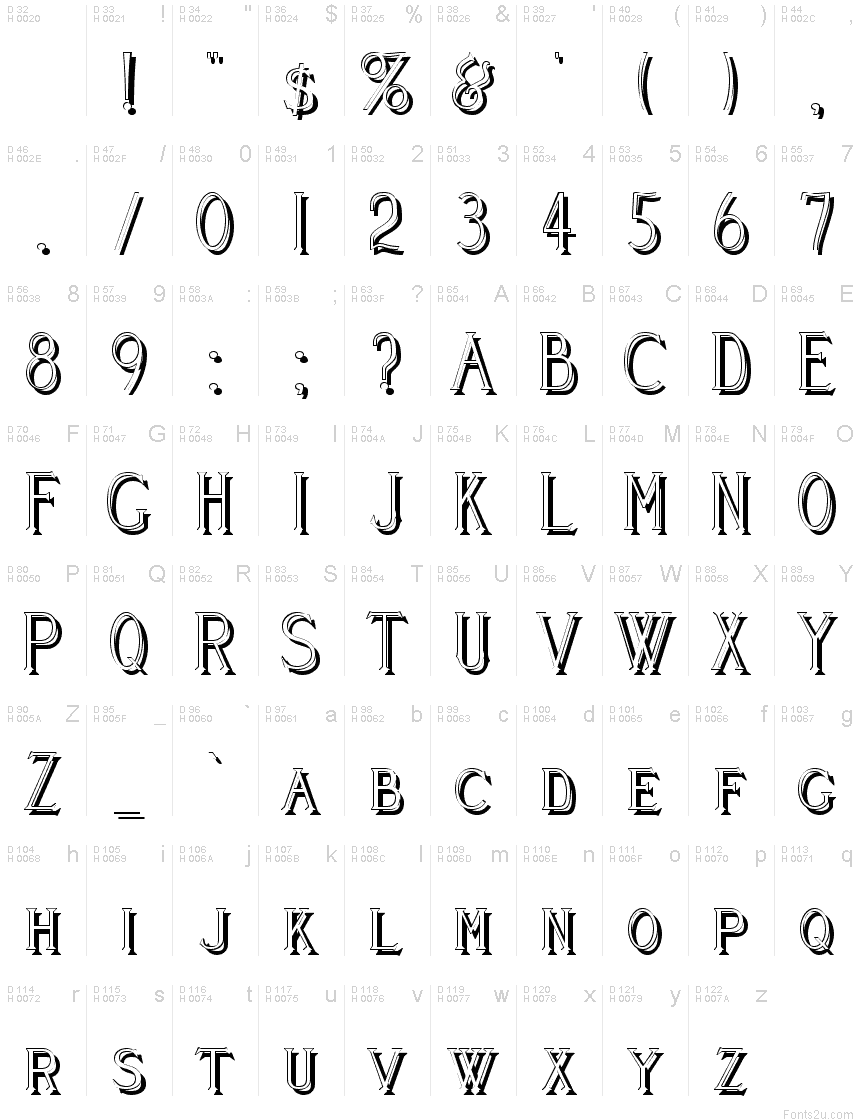
Cleaver's_Juvenia_Shadowed
Cleaver's Juvenia Shadowed od PJL to darmowy, dekoracyjny krój szeryfowy, który przywołuje dramatyczny klimat vintage. Wysokie, eleganckie wielkie litery o białych wnętrzach i ciemnych, wyrazistych krawędziach nadają każdemu słowu wielowarstwowy, cieniowany efekt, dzięki któremu napis niemal „wychodzi” z kartki. Rytm kresek jest teatralny, ale uporządkowany, co pozwala łatwo tworzyć efektowne nagłówki bez utraty czytelności.
Dzięki Cleaver's Juvenia Shadowed Twoje nagłówki natychmiast zyskują klasyczny, wyrazisty charakter, idealny na plakaty, okładki książek, logotypy, opakowania w stylu retro, szyldy czy zaproszenia. Strukturalne szeryfy zapewniają czytelność w większych rozmiarach, a cieniowane kontury dodają głębi i osobowości. Ten darmowy font doskonale łączy się z prostym krojem bezszeryfowym w tekście głównym i lubi hojne światło między literami, które pozwala mu „oddychać”.